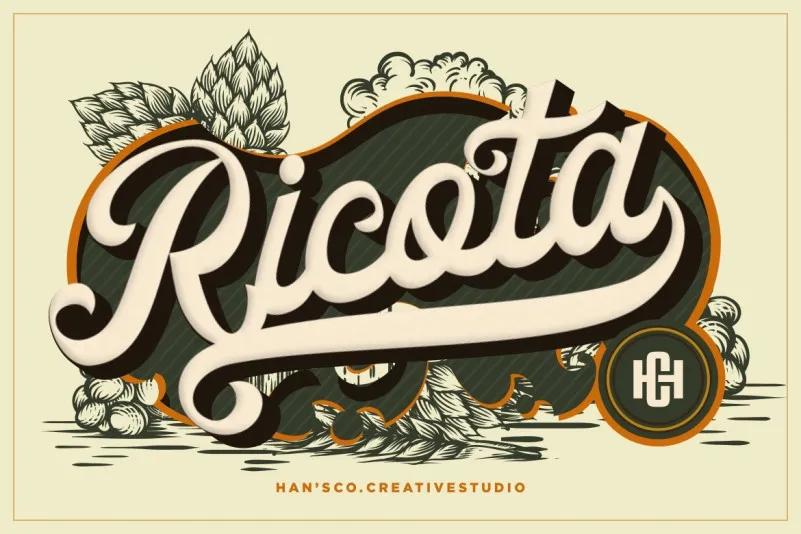
Ricota Font – Download Grátis
A ‘Ricota Font’ é uma excelente opção para quem busca uma tipografia com forte personalidade e um toque de nostalgia. Com seu desenho bold e script, esta fonte se destaca por sua elegância e sofisticação. Ela perfez a necessidade de adicionar um estilo único em elementos como logotipos, camisetas, cartas de convite, embalagens de produtos ou anúncios publicitários. Perfeito para designers que buscam dar vida à marca através de seu nome e logo, esta fonte inclui letras maiusculas e minusculas, pontuação, símbolos e números. Além disso, a inclusão de alternativas estilísticas e ligações pode proporcionar ainda mais versatilidade na criação de identidades visuais. Seja para um projeto web ou uma campanha publicitária, ‘Ricota Font’ oferece o poder de transformar textos em elementos visuais memoráveis.